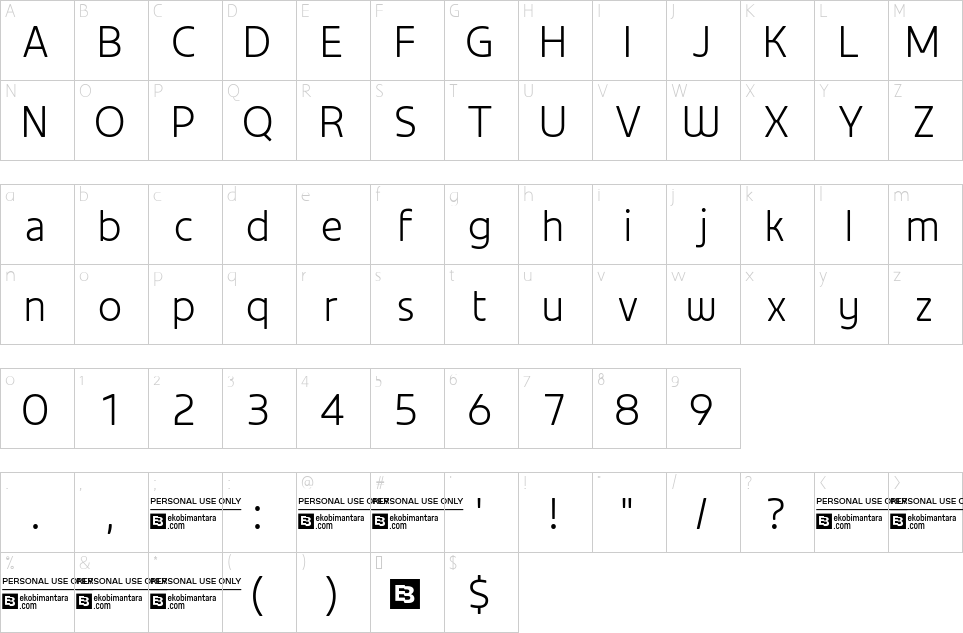
Descubra a Gresco Font, uma elegante e moderna opção para seus projetos digitais. Criada pelo talentoso Eko Bimantara, esta fonte oferece um toque sofisticado aos textos e gráficos que você cria. Sujeitável tanto para uso em ambiente Windows quanto no Mac, a Gresco Font foi desenhada para dar vida aos seus projetos com estilo. Com apenas 87 downloads desde seu lançamento, ela prova o valor do design atento e cuidadoso. Experimente a Gresco Font e adicione um toque único à sua coleção de fontes.